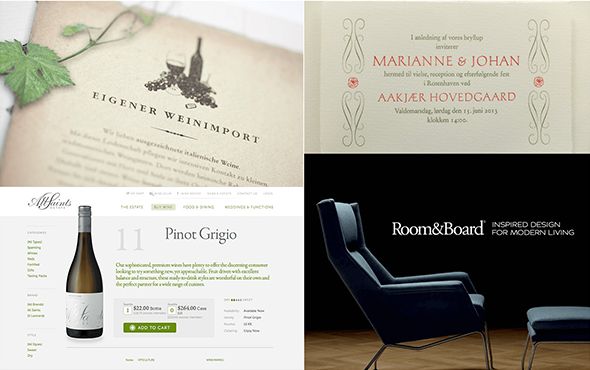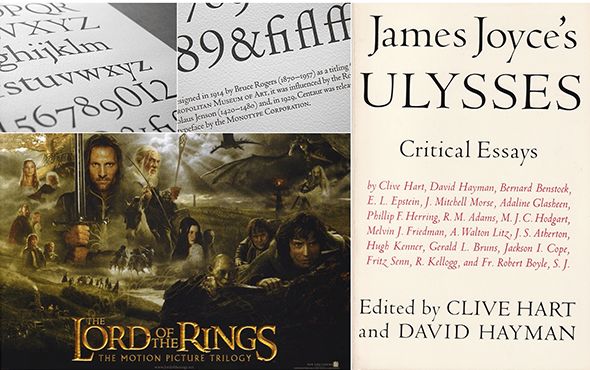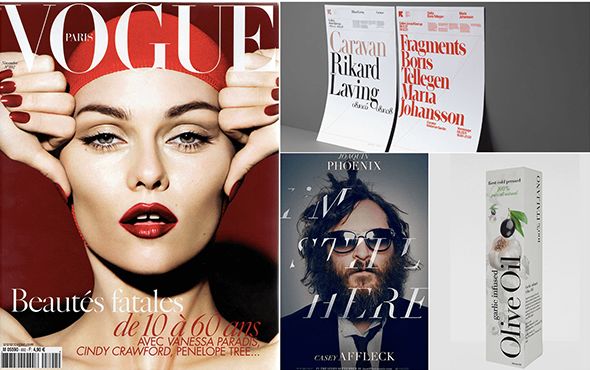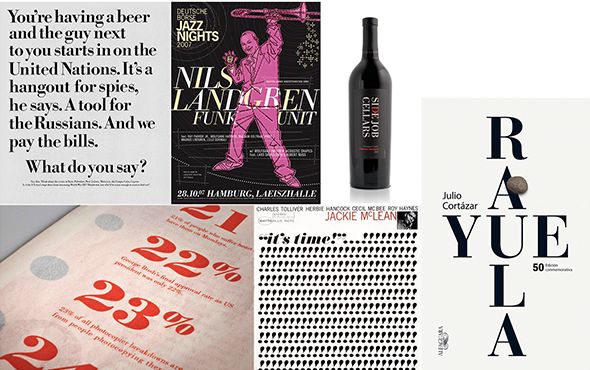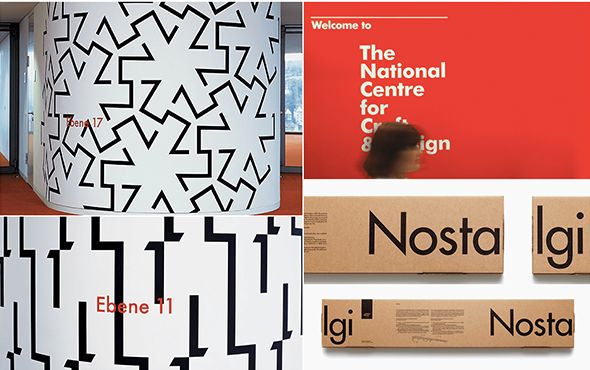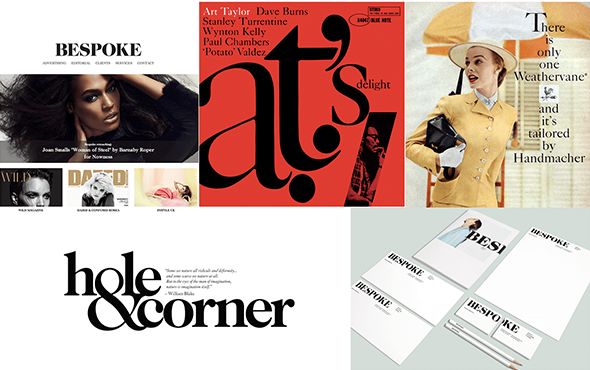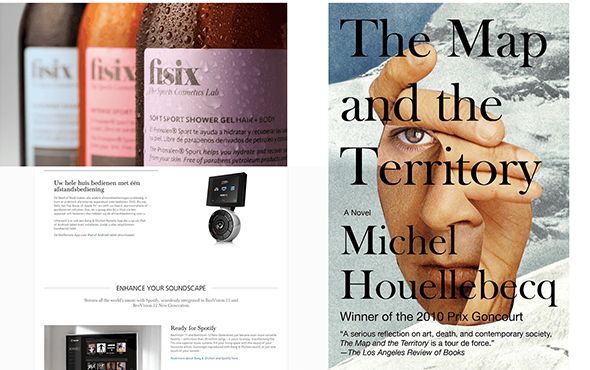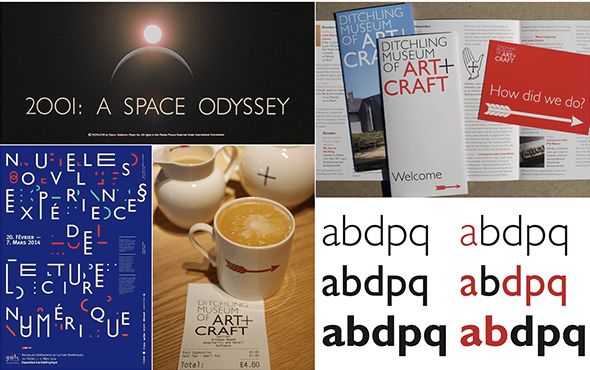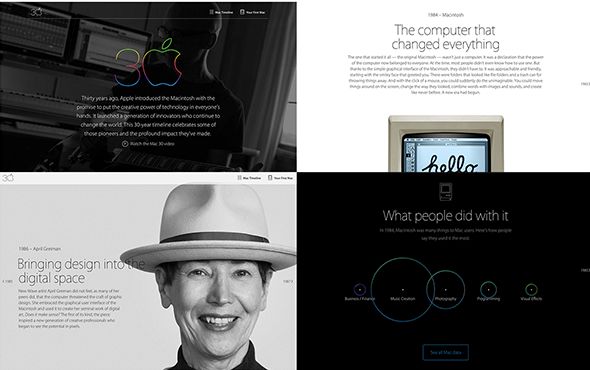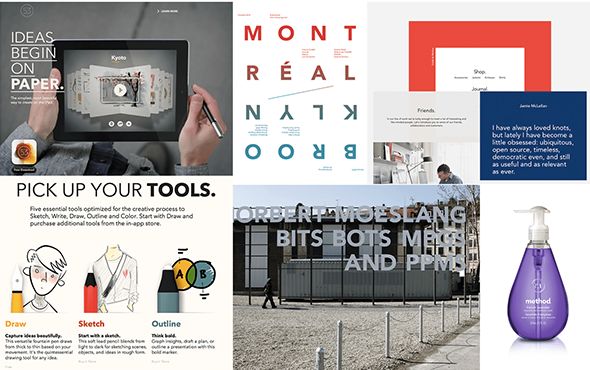
英文字体的分类,一些经典的英文字体推荐
字体是视觉设计中最重要的传达元素之一,字体本身的视觉特性和品质影响着信息传递的质量,英文字体有自己非常完善的系统,如果要精通则需要从字体的历史与形成,文化属性细细研究,限于文章篇幅,这里只从个人的感受出发写一些更偏向于应用的内容。
英文字体的
分类
英文文字大致分成三类,衬线体,无衬线体和其他字体。其他字体包括哥特体,手写体和装饰体,这些字体在我们工作中使用相对较少,所以重点介绍衬线体和无衬线体两大类。
衬线体的历史比较悠久,是古罗马时期的碑刻用字,适合用于表达传统,典雅,高贵,距离感。
衬线体可以分成两类:类似手写的衬线体叫“旧体”,笔尖会留下固定倾斜角度的书写痕迹,O字母较细的部分连线是斜线。旧体并不意味过时,传统书籍正文通常用旧体排版,适合长文阅读。
比例工整,没有手写痕迹的衬线体叫“现代体”。O字母较细部分连线是垂直的。体现了明快的现代感,给人冷峻、严格的印象,这种衬线体缩小后文字易读性比较差,一般在标题上使用。
衬线体还有另外一种分类方式,根据衬线变化可以分成三类:具有特定曲线的衬线为“支架衬线体”,连接处为细直线的是“发丝衬线体”,厚粗四角形的“板状衬线体”。
支架衬线体是旧体中最常见的字型,在衬线体中相对亲切、传统。比较常见的字体有Times New Roman,Baskerville,Caslon,Georgia。
发丝衬线体是现代体中常见的字型,具有明显现代感,不适合磅值小的字体。比较常见字体有Didot,Bodoni。
板状衬线体比较有力,是19世纪到20世纪初用在广告牌上的文字,多用于标题,具有怀旧气氛。
无衬线体相对衬线体更加亲和,现代。从类别上大致可以分成四类:Grotesque, Neo-grotesque,Humanist和Geometric。
Grotesque是最早出现的无衬线体,所以保留了一些衬线体的特征,比如小写字母g的写法不一样,数字1下方有粗衬线。
Neo-grotesque包括很多常用字体,Helvetica,Arial,Univers,不带情绪,冷静简洁。
Humanist有一点书法感,给人温暖的典雅气氛,有一点女性气质,识别度非常好,网站正文字体常用。
Geometric字体趋近几何形状,例如字母O非常像正圆,字母a是半圆加一个尾巴,易读性不好所以不适合用在正文,但是这类字体有非常强的设计感。在某些需要突出设计感的场合用磅值大的字体效果很好。
个人感觉从趋势上而言humanist和Geometric使用率越来越高,尤其是web端Humanist慢慢在侵蚀Neo-grotesque的领地。
经典字体
推荐
当我们不确定用什么字体的时候不妨先确定什么类别的字体最合适,衬线还是非衬线,人文体还是几何体,确定好了之后再多考虑看看一些经典字体是否可以使用,下面推荐一些经典字体。
Centaur具有史诗般正统风格,特别适合用于表现年代悠久。具体排版时注意合字和老式数字的使用。
复古传统,没有强烈个性,十分易于阅读,因为太流行所以很多大的公司都做过Garamond复刻,苹果电脑里有系统字Garamond以及Adobe所制作的Adobe Garamond Pro。 如果是希望web上使用,可以考虑EB Garamond。
美国独立宣言用字,是活字时代的大热字体。很多公司也做过Caslon复刻,现在的使用也非常广泛。
过渡期罗马体(旧体到现代体)的代表性字体,非常经典,给人古典、高贵的感觉。
现代衬线体,发丝衬线。特点是强烈的笔画粗细对比和水平衬线,时尚,现代,优美。
与Didot类似,适合大字体表现,相对Didot来说硬朗一点。
这款字体是很早出现的无衬线体,所以带有古风,笔画粗狂有力,具有男性化感觉,适合表现强有力。Web字体可以考虑Oswald。
Futura是拉丁语未来的意思,现代且具有几何特征,感觉是现在的主流大热字体,尤其是要突出时尚,设计感的时候可以使用。制作过程中受到包豪斯运动的影响。是LV的商标用字,也是现在很多杂志的首选字体。
英国风格的代表字体,具有古典风格的骨架,但是又有很强的科技感和未来感,字体外形偏几何,但是是humanist字体,相对futura会柔和一些。
有古典气息,笔画两端比较粗中间比较细,气质优雅。时代周刊的字体更换,雅虎2013年使用Optima作为全新标识的设计基准都证明了这款字体的热度。
Grotesque字体,比Helvetica更加简练。字体家族非常全面,所以搭配使用很方便。
Humanist字体,很早就已经流行,随着苹果的广泛使用更加引人注目,笔画柔和简洁。
字形简洁,现代,虽然也有几何特征,但是不失人情味。Avenir是法语未来的意思,对同样未来含义的Futura是一种挑战,放大x-height,降部拉长,使得文字的易读性明显提高。字体家族也很完整。
最后提两句Helvetica,内部分享的时候很多设计师问到为什么没有作为一个推荐字体在这里列出,一方面是因为Helvetica已经作为现代字体中的经典字体被应用得非常广泛了,并不缺乏关注。另一方面Helvetica是Neo-grotesque字体,结构严谨,没有情绪导向,提供着强烈的安全感,好像怎么用都不会错,这是个优势也是个劣势,当我们的设计有比较明确的受众群体或者设计对象有比较明确的气质的时候能够寻找到有同样气质的字体会是更优的选择。
适合长文阅读
的字体
无衬线体中适合长文阅读的文字一般是Humanist,衬线体中适合长文阅读的文字一般是支架衬线体。下面列几个个人觉得比较适合排长文的字体。
无衬线体:Lucida Grande, Roboto, Open Sans
衬线体:Georgia, Droid Serif, Cambria
适合长文排版的字体还有很多,比如无衬线体中的Lucida Sans,Geneva,衬线体中的freight text,看一些比较好的设计的时候不妨多留心一下字体用的是什么。
字体应该如何
搭配
字体搭配总体的原则是一致性加对比性。一致性指的是选择调性和情绪一致的字体。比如现代罗马体搭配几何无衬线体,古典罗马体搭配年代比较久远的无衬线体。字体的情绪表达需要统一,严肃的字体并不适合搭配随意的字体。
对比性是指字体之间要有较明显的差异,不能感觉很像,分不开差异。
对比性也可以用很多种方式达成,上面列出的不同字体搭配是一种,不同的字重和不同样式都可以,用字重来强调对比的话最好不要选择相邻等级,用隔一个等级的字款搭配。
最简单的搭配方式就是用同款字体创造对比,另外一个很保险的方法是选择包含有对比性字体的字体家族,比如ITC Stone Sans Std和ITC Stone Serif Medium以及Freight Sans Pro和Freight Display Pro。很多字体家族是同时包含称衬线体和无衬线体的,它们在设计初始的时候就有相同的骨架,所以排版起来非常协调。